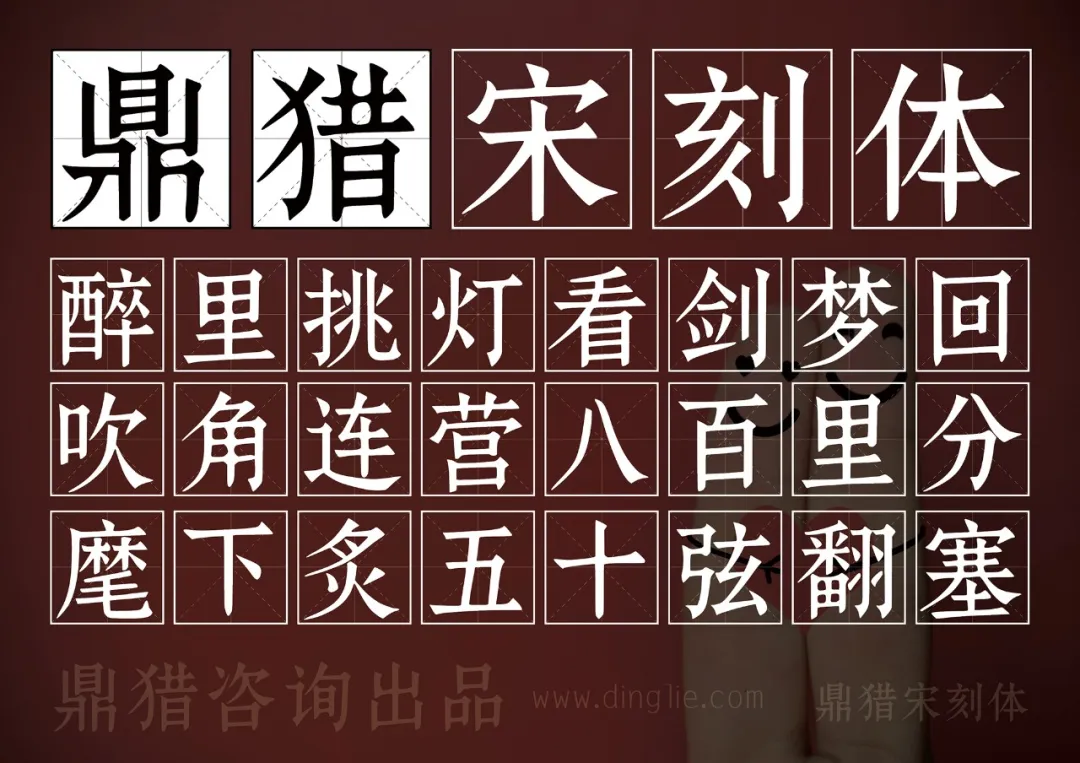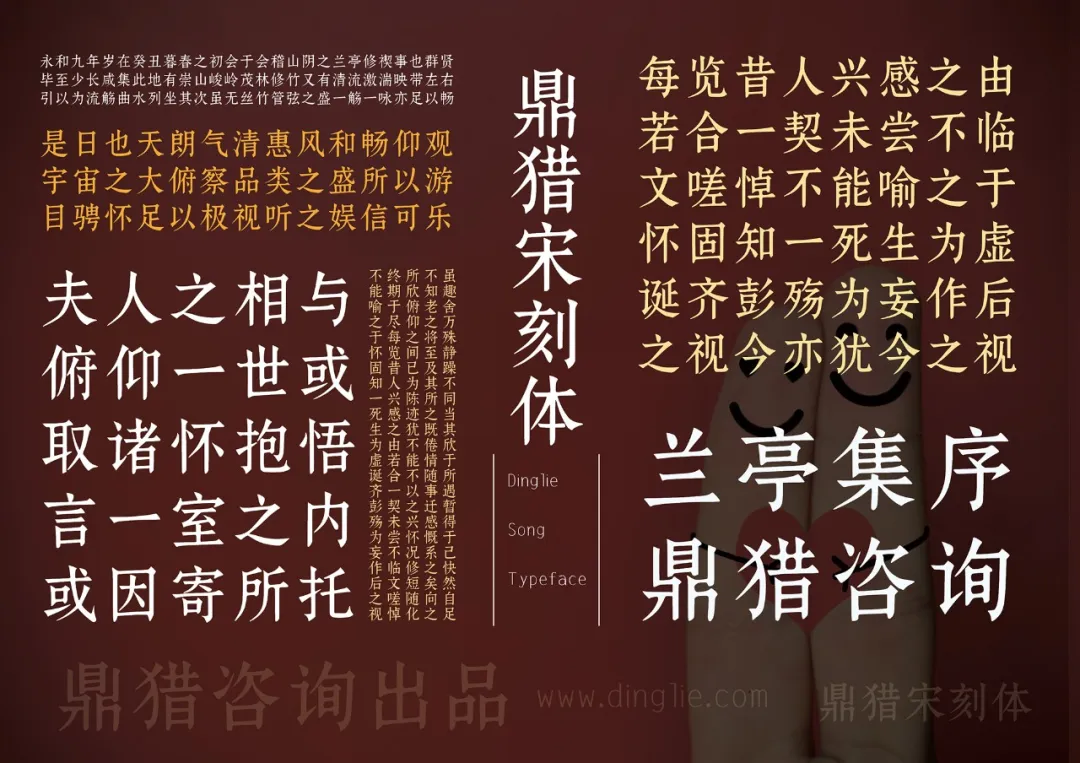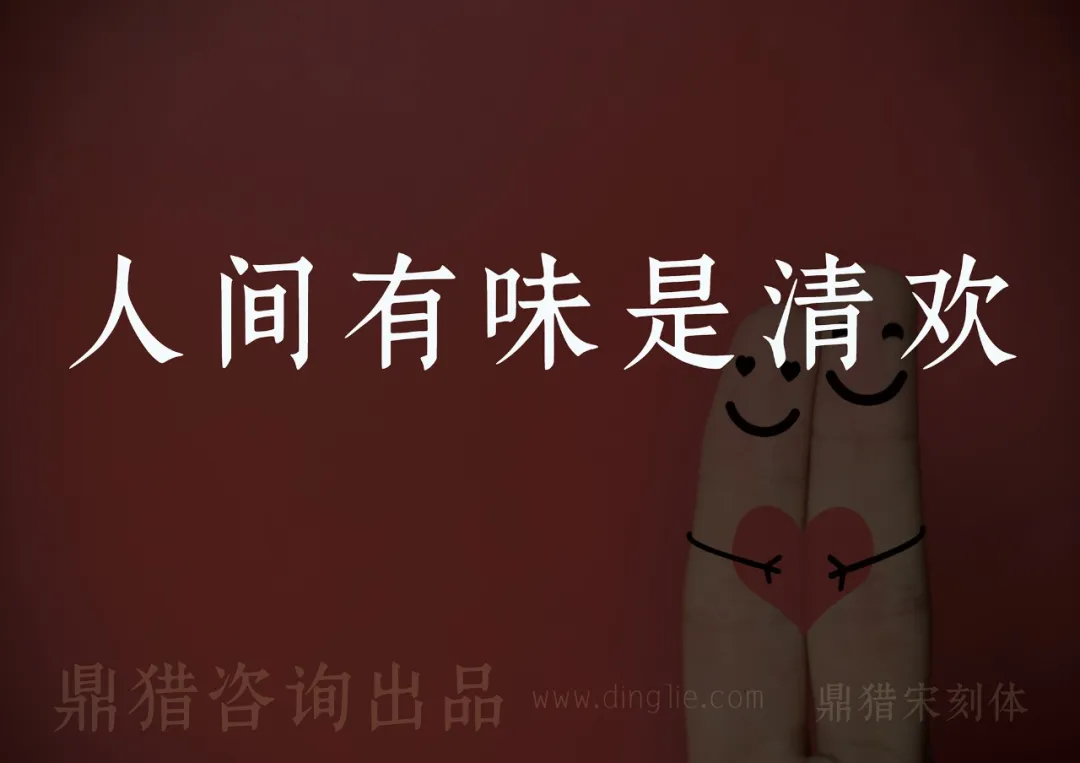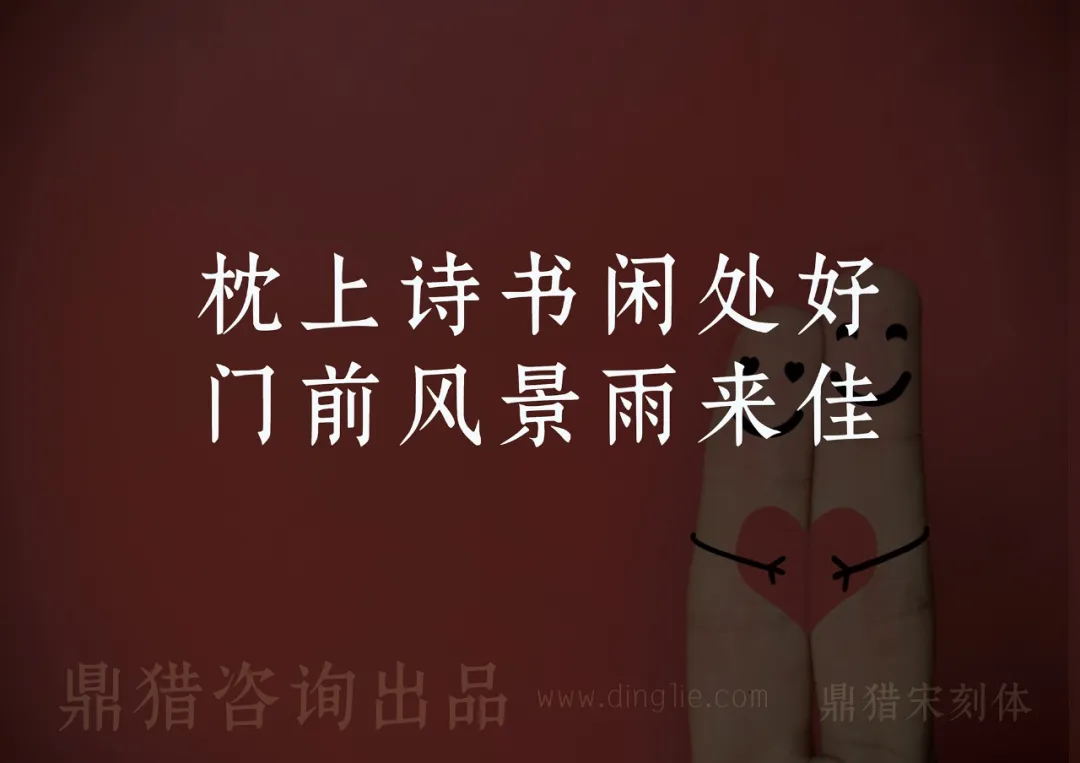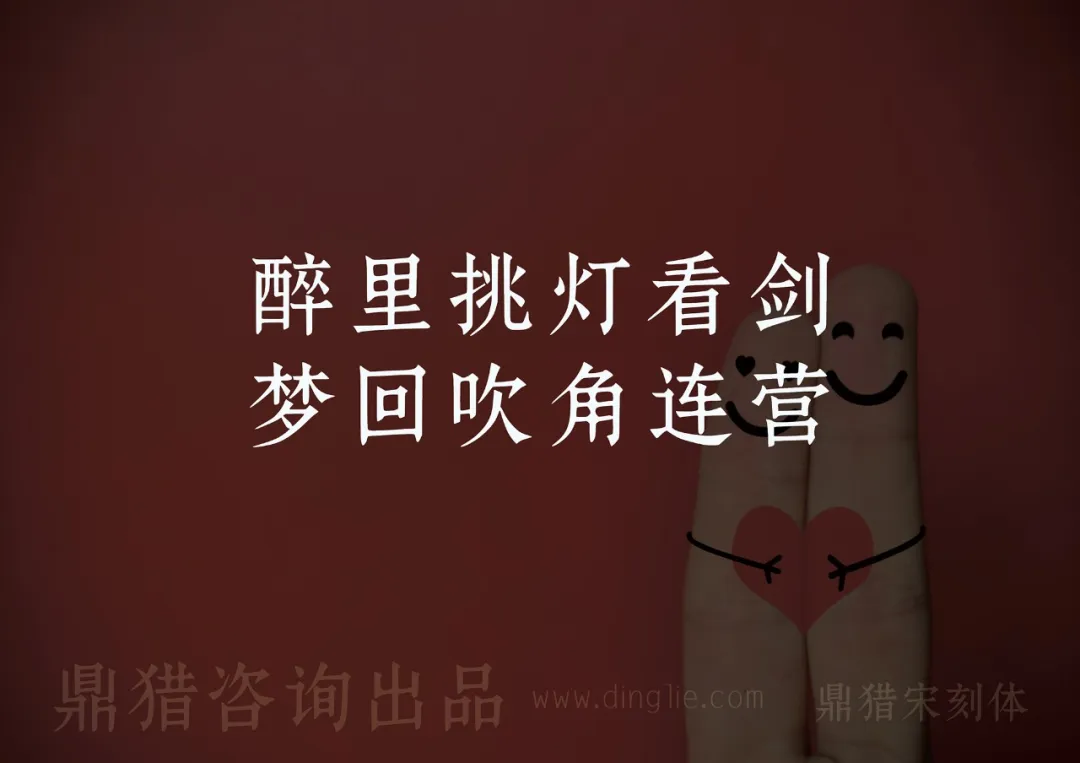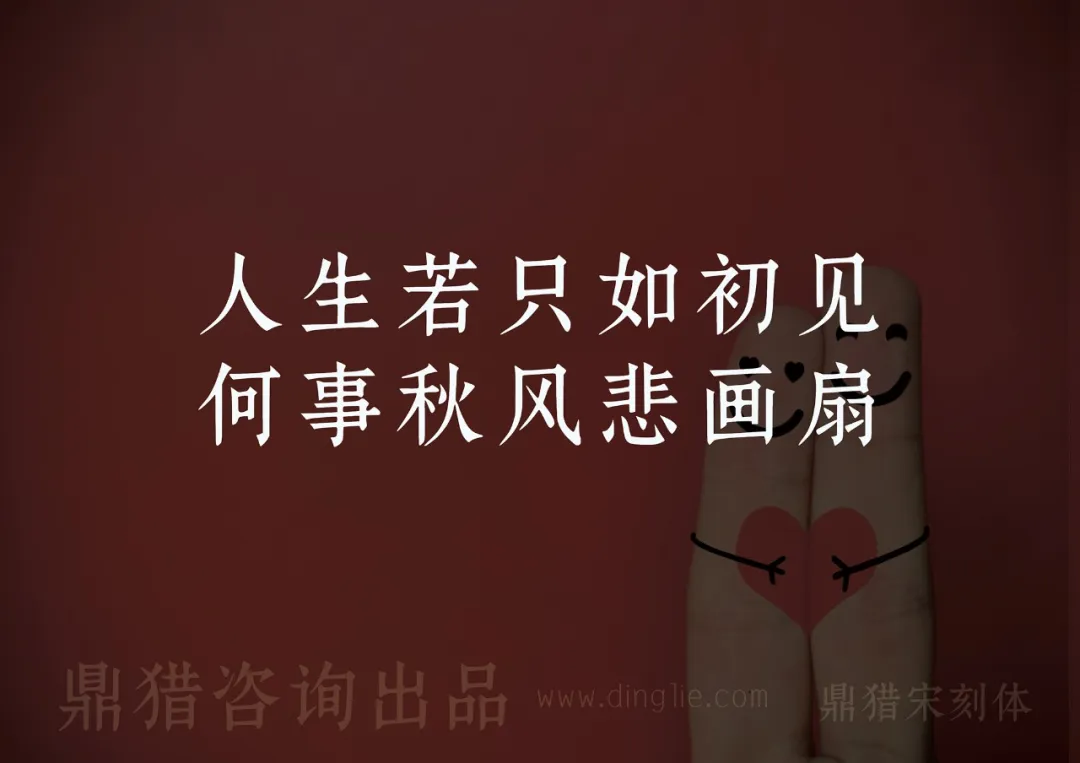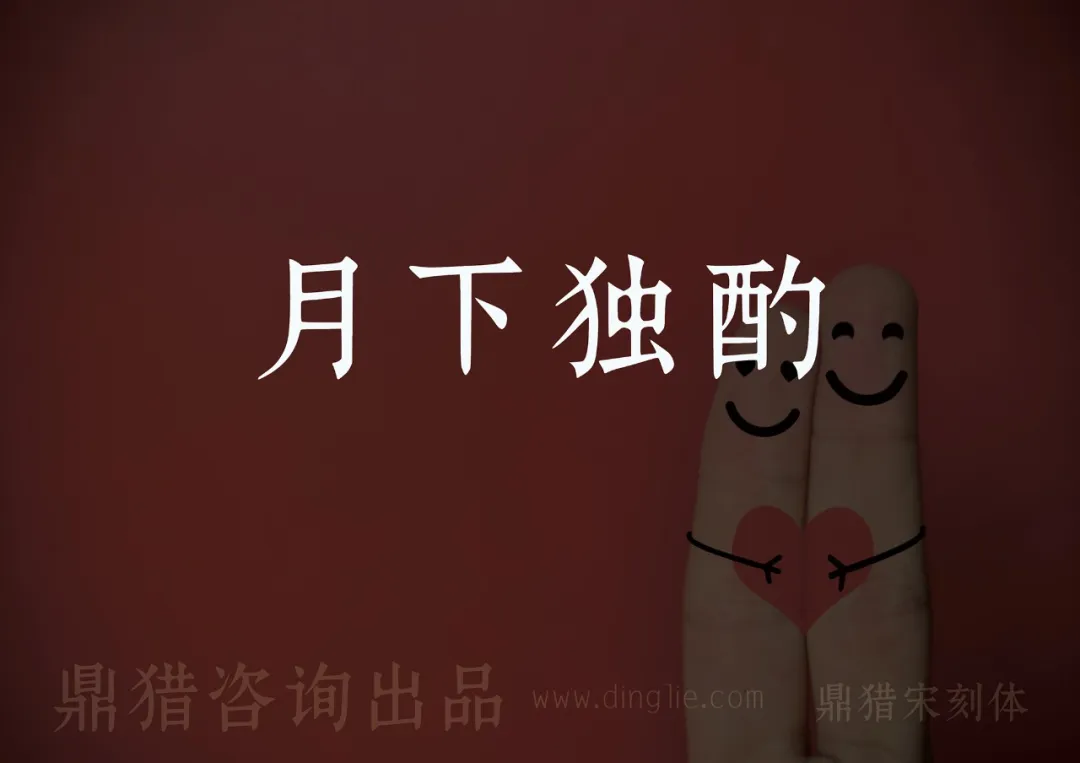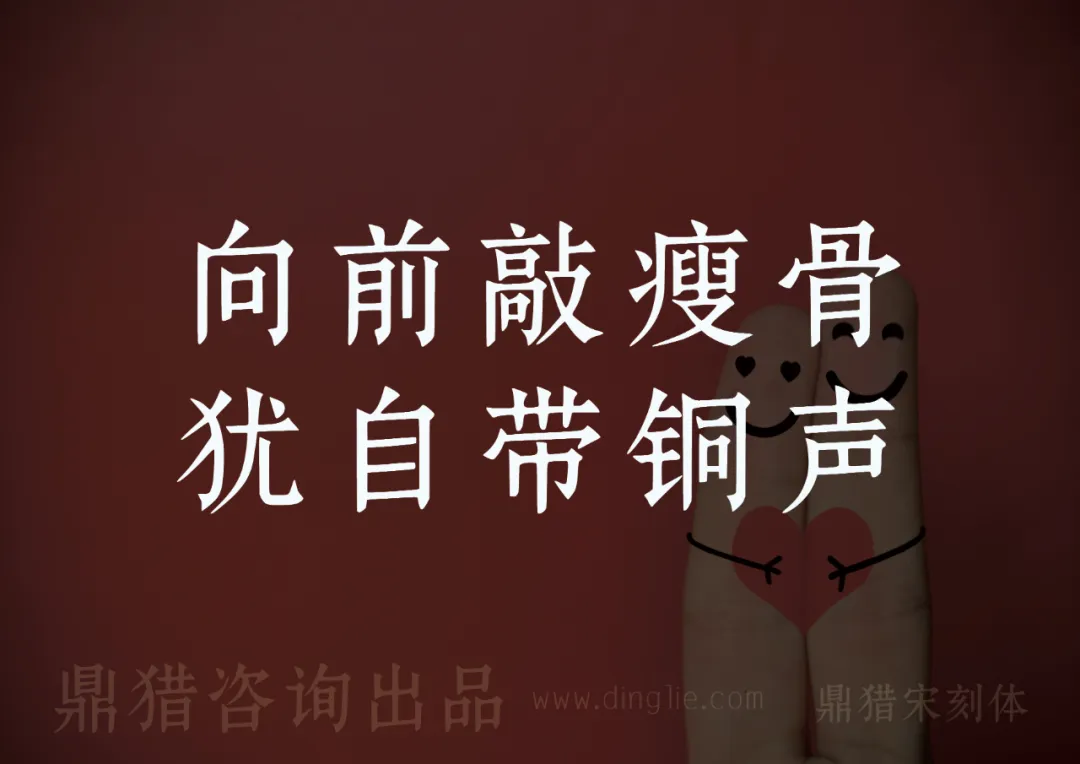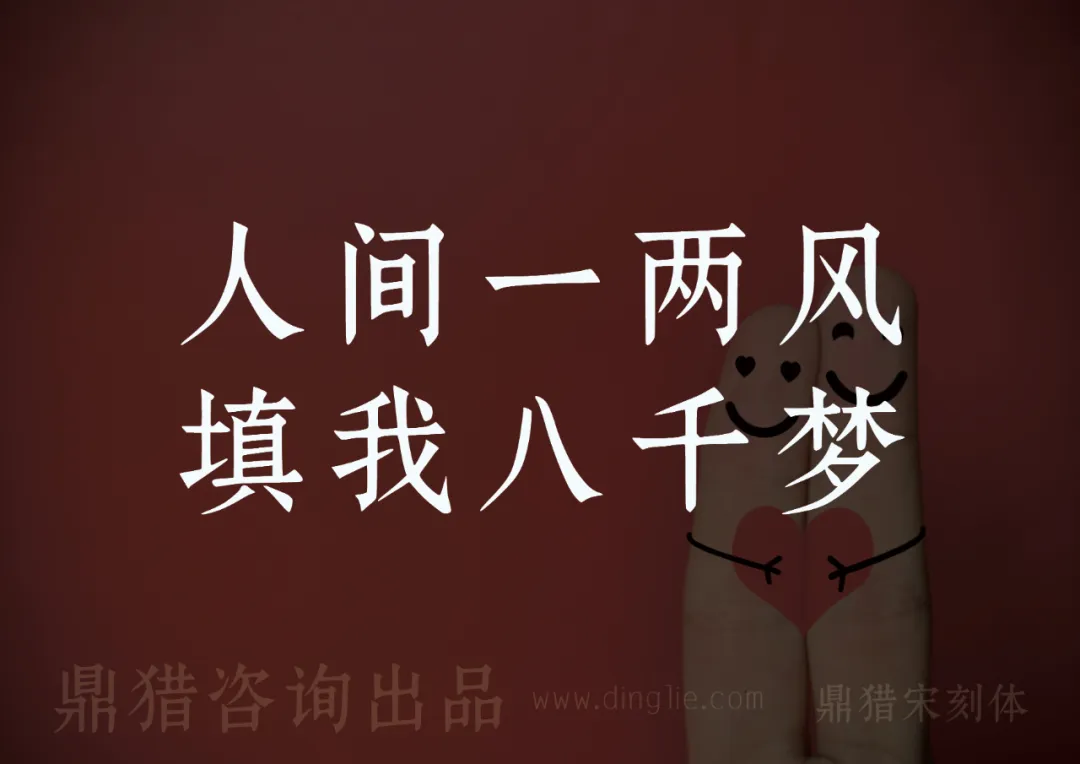
鼎猎宋刻体,源于结体谨严,笔画顿挫感明显的宋刻本。鼎猎宋刻体排版时文理坚致有韧性,版式疏朗雅洁,适合美食餐饮、文化艺术展览、企业文化,以及封面杂志海报、餐饮茶饮、美妆护肤等各个行业。
考虑到字体应尽可能满足各类型应用场景,
鼎猎宋刻体以简体中文汉字编码国家标准(GB2312编码)为标准,
共计设计了多达7415个字符,其中汉字6769个。
可以满足绝大部分印刷设计等要求。
以下为鼎猎宋刻体的应用展示,
您还可以用来用于制作各类海报和包装。